ライナーペン。
では、今日からペンの章です!
ペンは、日本国内では100円前後から様々なものが手軽に購入出来ますね。
つけペンほど敷居が高くないのも魅力のひとつかな。
普通のボールペンでも大手メーカーさんのはかなり描き味が良いので、そちらを使用して絵を描くのもいいでしょう。
自分で試してみて、使い易いなと思うものを使えばオッケーですね。
講釈はともかく、手始めは
絵やデザインに特化したマーカーならこれ!と言う日本が誇るが材屋Tooさんのコピックシリーズのライナーペンです。
普通にインクは黒で、割とみんな持っているタイプの見本になりましたが。
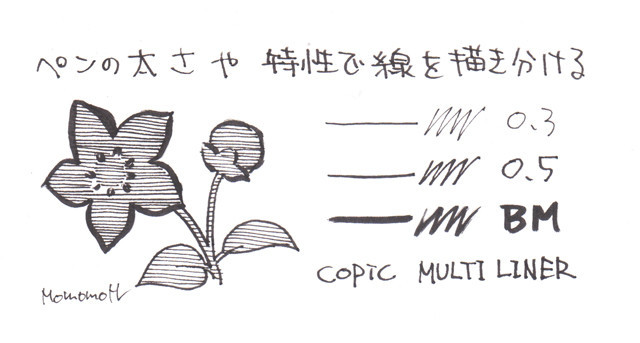
*BMとは、ブラシタイプのM
コピックシリーズは様々な種類が出ておりますが、これはライナーなので線を描くのに特化したものですね。
他社でもピグマとか細い線(0.1とか)がひけるものが出ています。
この手のライナーは、均一な線になるのでそれが個性であり強み、逆に線の強弱を出したい場合はやはりつけペンが向いています。
けれど、上の図にもあるBMのような筆ペンのように描けるペン先のものも出ているので、それを使う事も出来ます。
ただ、ブラシタイプはつけペンよりも筆に近い使い勝手ですので、厳密に言えばやはり違うかな?
こういう均一(フラット)な線のタッチはつけペンと表情が違うので、好みや描く対象によって使い分けするといいでしょう。